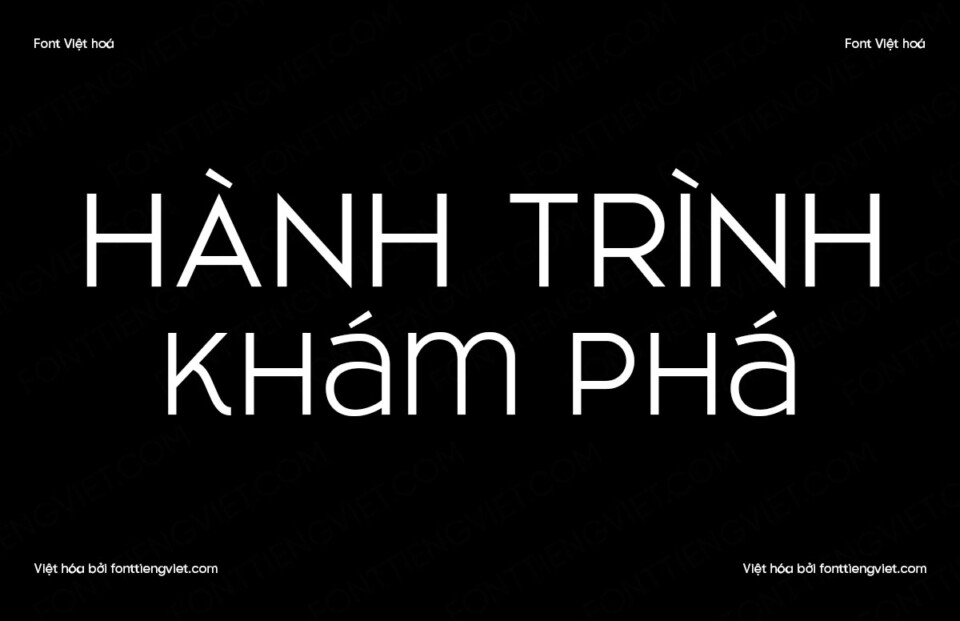
Khám phá bộ Font Việt hóa 1FTV VIP Cherione sang trọng cho thiết kế trường họcGiới thiệu về Font Việt hóa 1FTV VIP CherioneTrong thiết kế đồ họa học đường, việc lựa chọn Font Miễn Phí phù hợp đóng vai trò quan trọng để truyền tải thông điệp. Bộ Font Việt hóa 1FTV VIP Cherione là một giải pháp hoàn hảo mang lại sự kết hợp giữa nét hiện đại và sự chỉn chu. Với các đường nét tinh tế, bộ font này giúp các bạn học sinh và thầy cô dễ dàng sáng tạo nội dung bài giảng hay báo tường sinh động.Ưu điểm nổi bật của Font Việt hóa 1FTV VIP CherioneThiết kế thanh lịch và dễ đọcBộ font sở hữu cấu trúc chữ cân đối, giúp văn bản trở nên rõ ràng trên cả màn hình máy tính lẫn bảng tin trường học. Sự phân chia tỷ lệ nét thanh nét đậm đồng đều giúp người xem không bị mỏi mắt khi đọc các đoạn văn dài.Hỗ trợ tiếng Việt hoàn chỉnhĐiểm cộng lớn nhất của bộ chữ này là hệ thống dấu tiếng Việt được trau chuốt kỹ lưỡng. Người dùng không còn lo lắng về lỗi font hay các dấu thanh bị lệch vị trí khi soạn thảo giáo án.Ứng dụng thực tế trong môi trường giáo dụcLàm slide bài giảng và thuyết trìnhThầy cô có thể dùng font chữ này để thiết kế tiêu đề slide, giúp bài học thêm phần lôi cuốn và thu hút sự chú ý của học sinh.Thiết kế Group báo tường và kỷ yếuĐối với các bạn học sinh, đây là lựa chọn tuyệt vời để làm tiêu đề cho các trang báo tường hoặc trang trí cuốn kỷ yếu lớp đầy kỷ niệm.Kết luận và tải vềBộ Font Việt hóa 1FTV VIP Cherione thực sự là một công cụ đắc lực cho mọi dự án sáng tạo nghệ thuật học đường. Để sở hữu ngay bộ chữ độc đáo này cho máy tính của mình, bạn hãy truy cập hệ thống Font Miễn Phí, Font Việt Hóa, Font Việt hóa 1FTV VIP Cherione để tải về hoàn toàn miễn phí và bắt đầu trải nghiệm ngay hôm nay.
Font Việt hóa 1FTV VIP Cherione